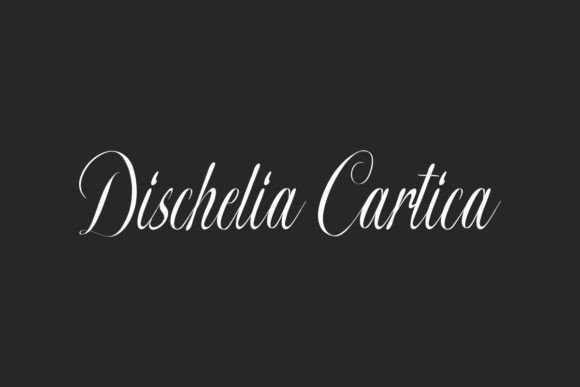
Dischelia Cartica
適切なデザイン要素を見つけるのは難しい場合がありますが、Dischelia Carticaは作品を即座に引き立てる優れたコレクションを提供します。
精密に作られたDischelia Carticaは、クリーンなベクター、滑らかなタイポグラフィ、そして安心のための商用ライセンスを提供します。
POD(オンデマンド印刷)製品、結婚式の招待状、またはソーシャルメディアのグラフィックを作成している場合でも、Dischelia Carticaは理想的です。